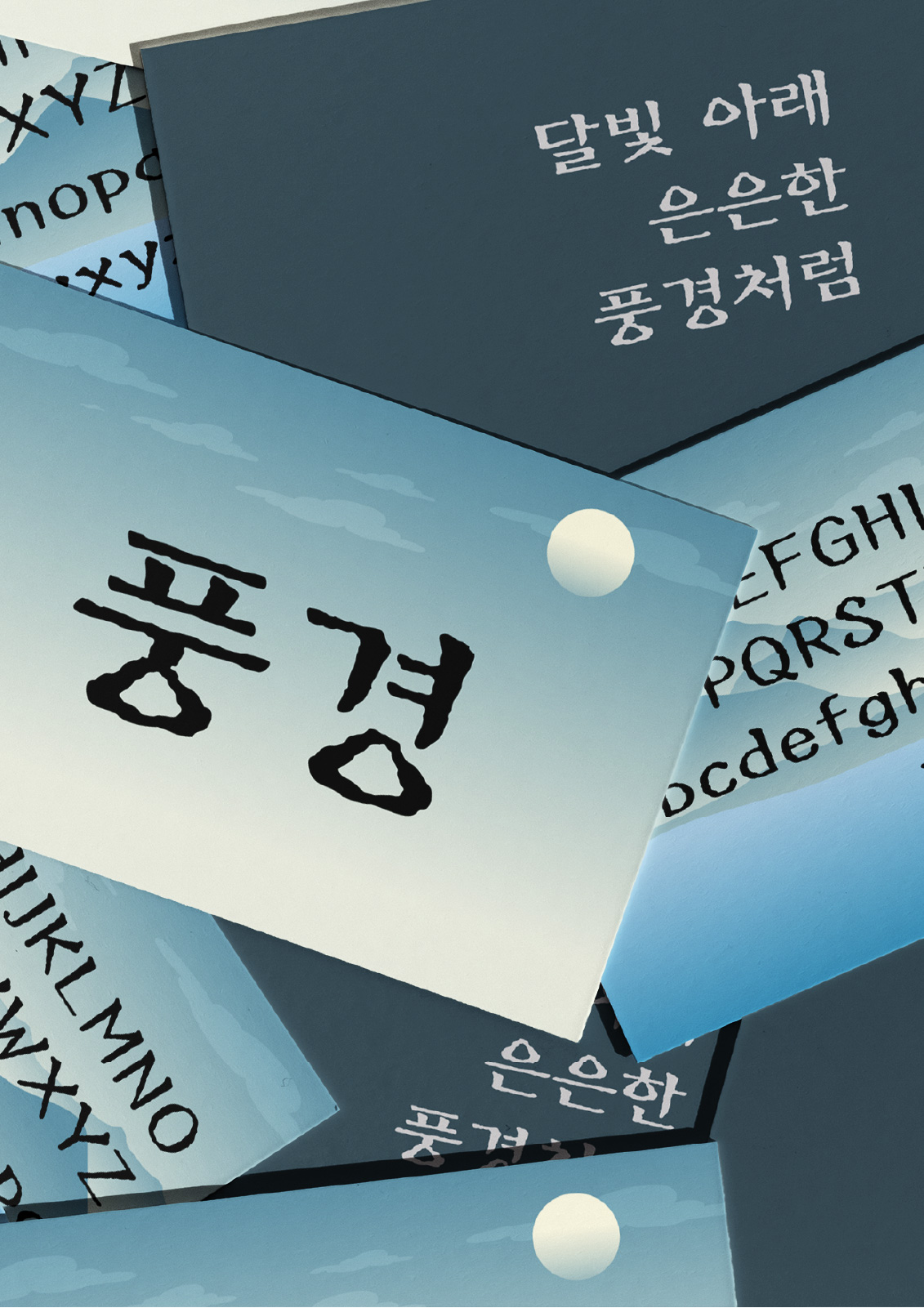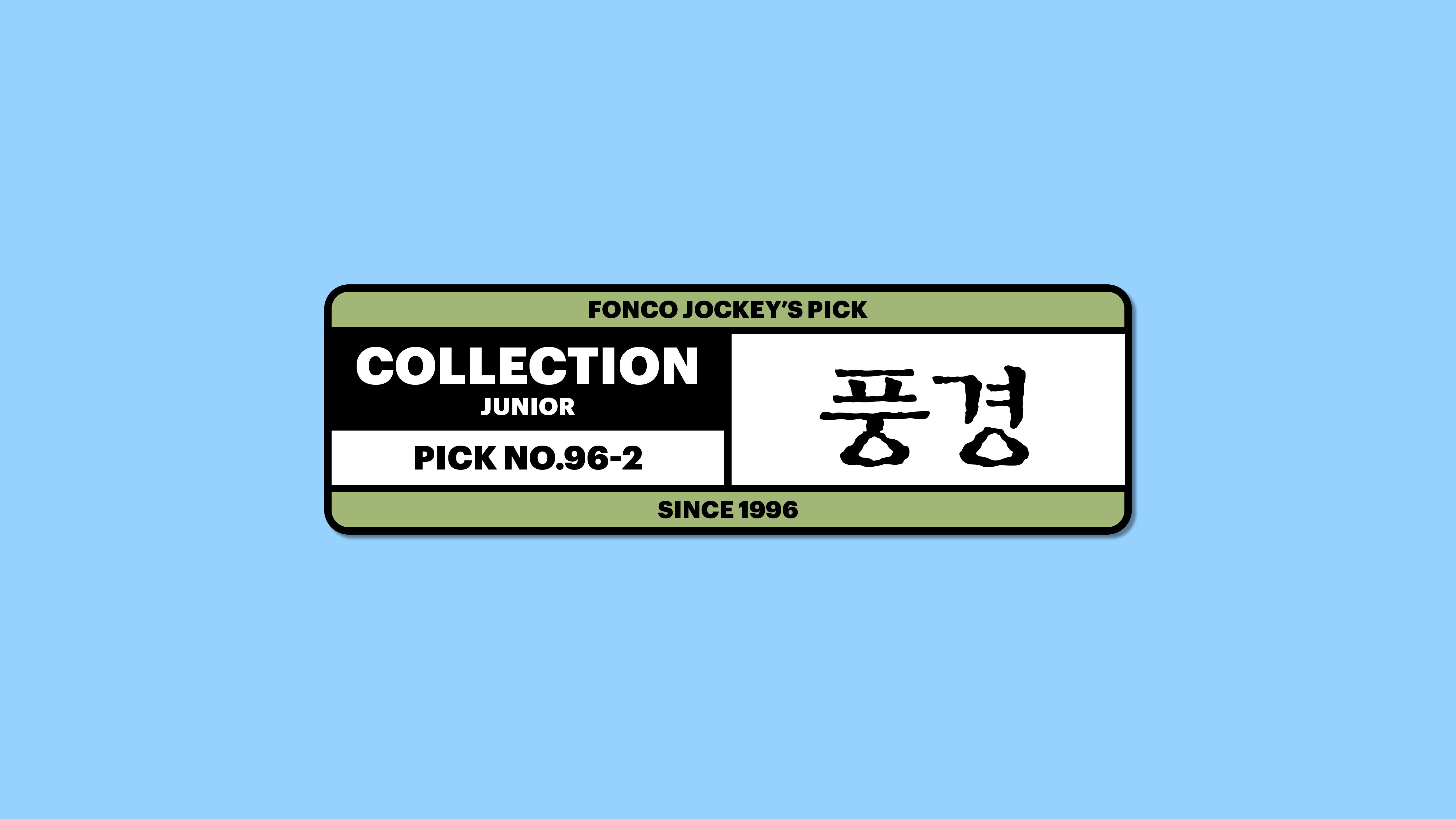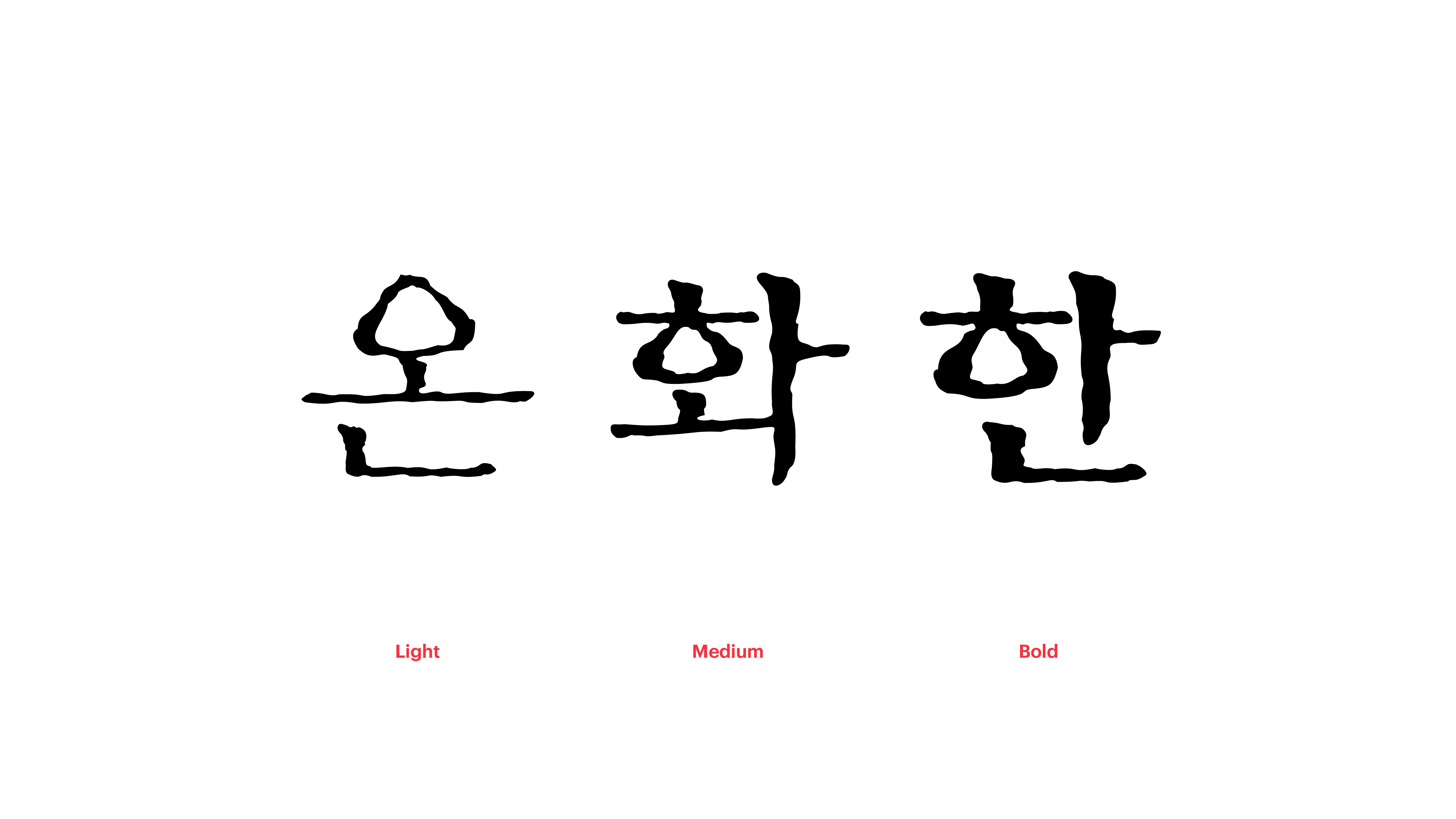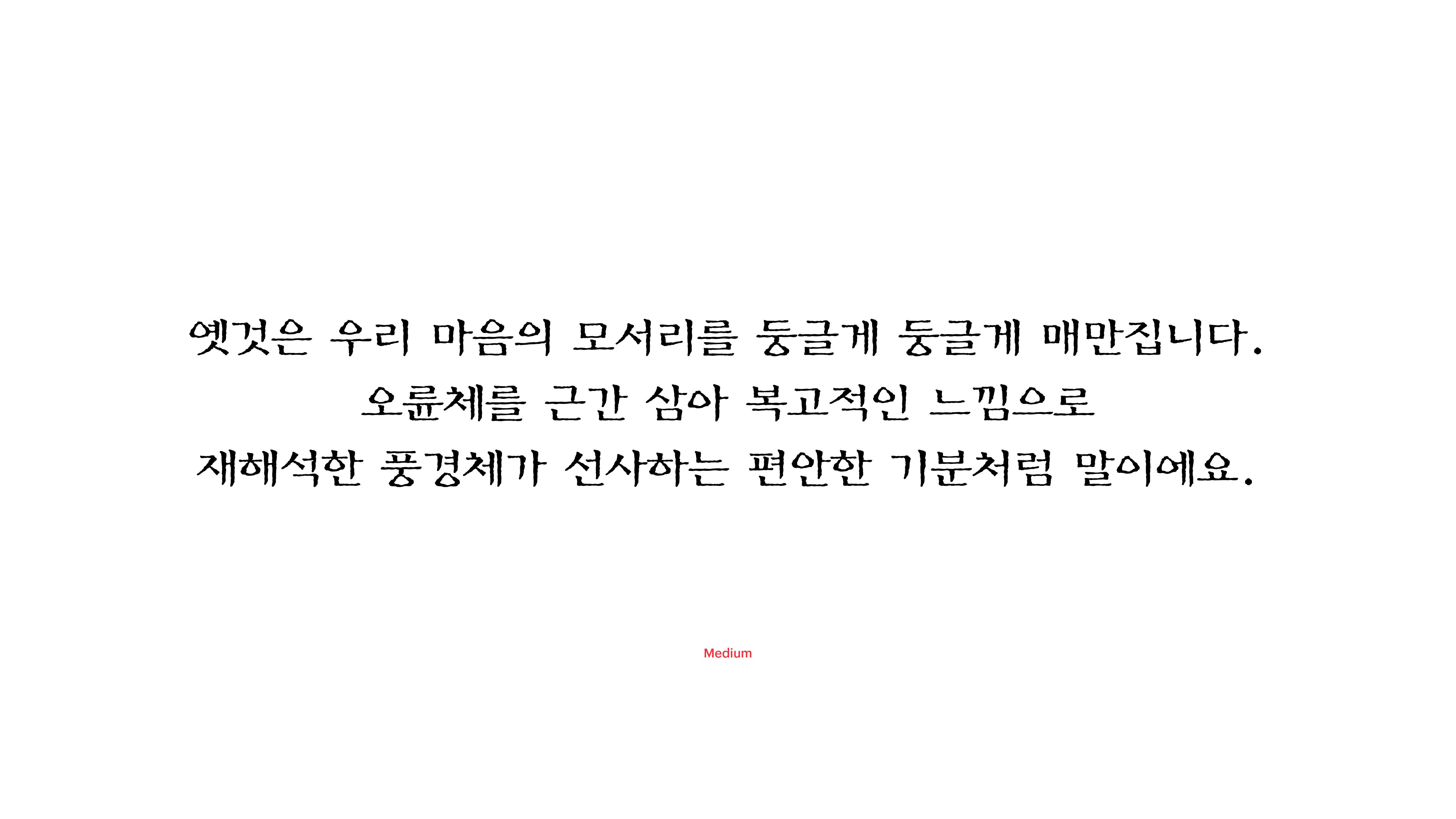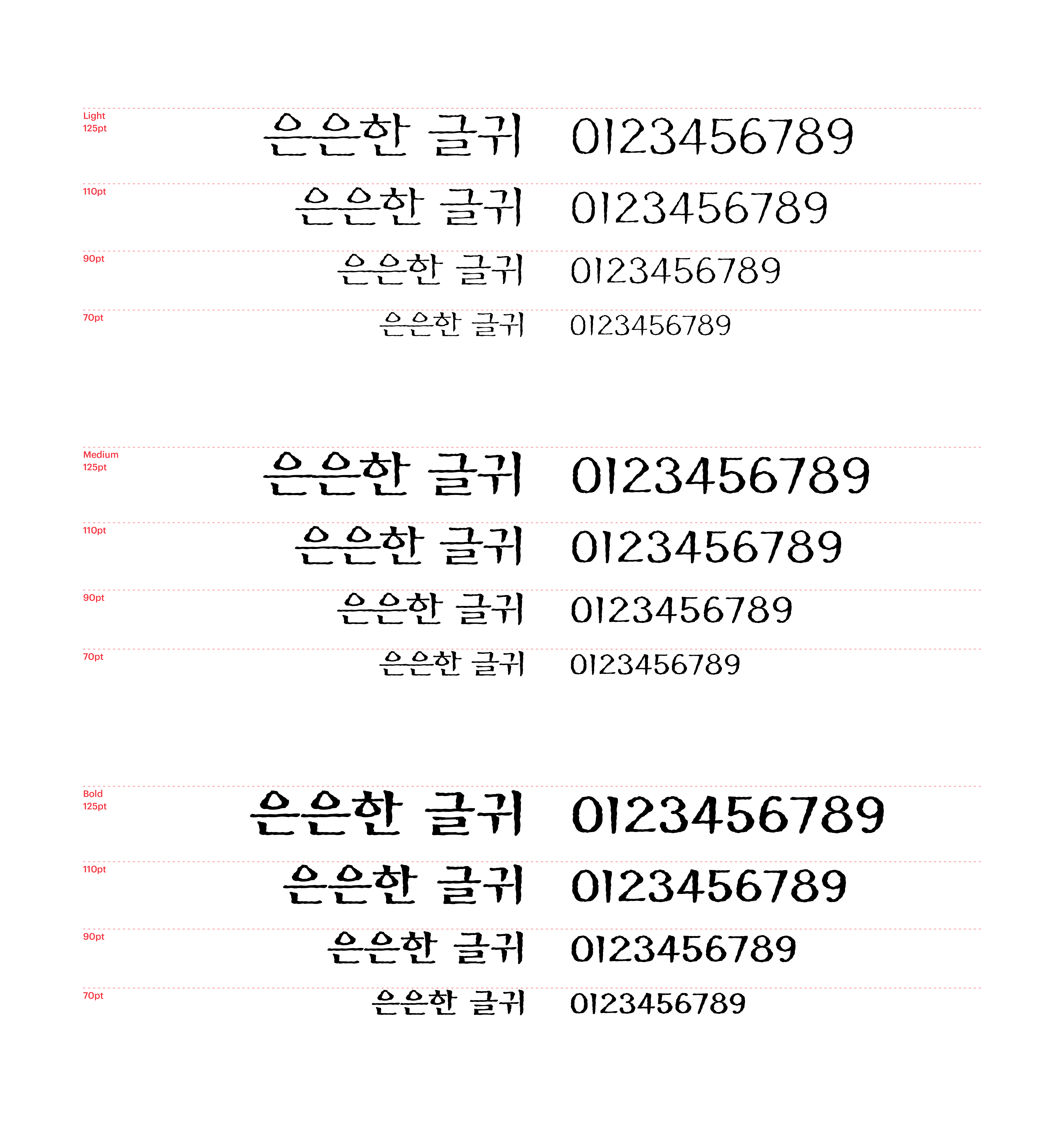
옛것은 우리 마음의 모서리를 둥글게 둥글게 매만집니다. 오륜체*를 근간 삼아 복고적인 느낌으로 재해석한 풍경체가 선사하는 편안한 기분처럼 말이에요. 어쩐지 마음이 불안정한 날, 명조체에 부드러운 질감을 더해 온화한 분위기를 풍기는 이 폰트로 은은한 글귀를 옮겨 적어보세요. 마음의 안정을 찾기 위해 따로 애쓸 필요가 없는 평온한 밤을 불러올 수 있을 거예요. *오륜체 : 한자와 함께 사용하였을 때 보기 좋은 한글 붓글씨체가 없다는 문제점을 해결하기 위해 고안된 한글 서체. 조선 시대 궁녀들이 사용하며 발달하였던 한글 궁체의 느낌과 중국 한자의 특징적 서체였던 명조체의 특징을 적절히 결합해 완성하였다. 조선 시대 대표 도덕서 오륜행실도를 기록하는 활자체로 사용, 조선 말기의 한글 활자들에까지 큰 영향을 끼쳤다.
Yoon 풍경